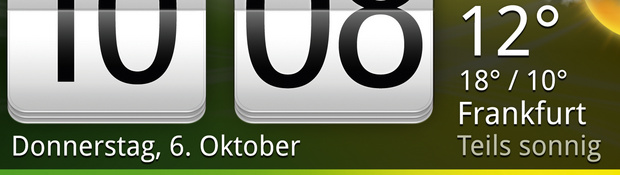
Eine namenlose Schrift
Deshalb kam sie mir so bekannt vor.
Oder vielleicht weil sie soviel Elemente von anderen bekannten Schriften hat.
Nun immerhin.